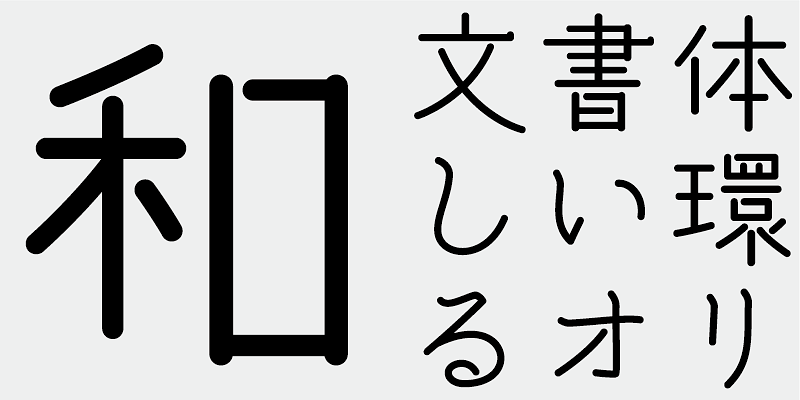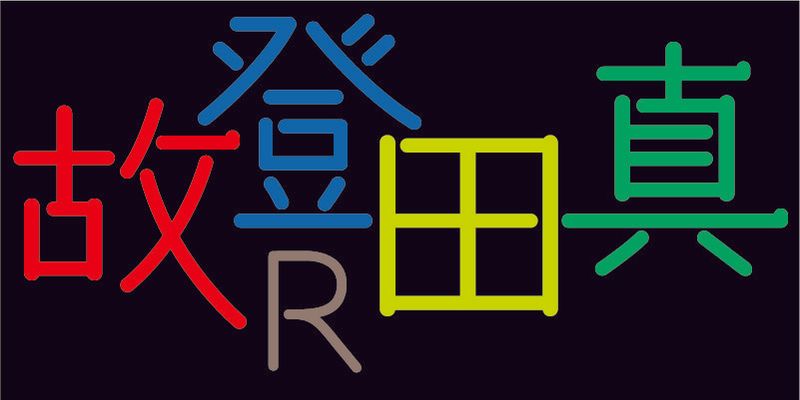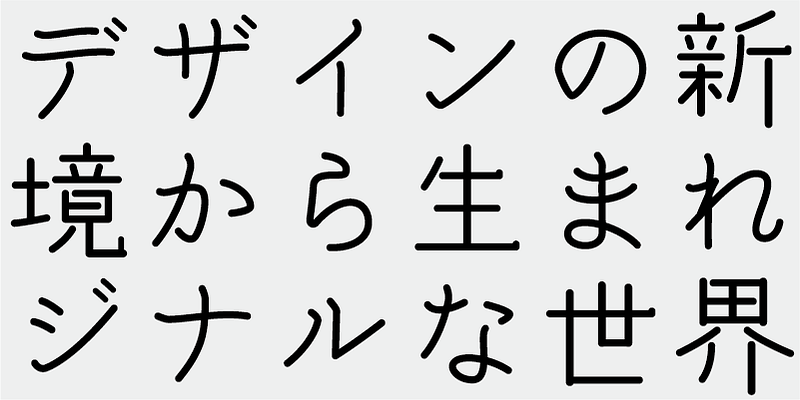
“캐주얼하고 편안한” 모양과 느슨한 문자 간격을 가진 둥근 모서리 고딕 서체입니다. 조판 텍스트는 시각적으로 부드럽고 차분한 표현을 연출합니다.
글꼴에는 Joyo Kanji List 및 Jinme-yo Kanji 문자의 2,286자 외에 가나 문자, 구두점, 라틴 문자 등을 포함한 206자가 추가로 포함되어 있습니다.
오늘날 일본어 글꼴 제작에서는 JIS 표준의 7,000자가 필수로 간주됩니다. 그러나 모든 글꼴에 정말 7,000자가 필요할까요? 사진 식자 시대에는 훨씬 적은 수의 문자가 필요했습니다. 독립 서체 디자이너 그룹인 FONT1000은 그 간단한 질문으로 시작했습니다. 일본어 서체에 필요한 최소 1,000자의 한자(표의 문자)를 선택했고 이를 지원하는 서체와 글꼴을 적극적으로 만들었습니다. 이 1,000자의 한자 문자 세트는 신문사, 출판사, 언어 연구 기관 등에서 수집한 문자 빈도 데이터를 사용하여 선택되었으며 가나 음절 문자 및 구두점도 포함합니다. FONT1000은 2001년에 25명의 디자이너와 25개의 서체로 시작했습니다. 현재는 130개의 서체를 보유 중이고 거의 40명의 멤버를 포함하도록 성장했으며, 더 많은 문자가 있는 글꼴 작업이 가능하게 되었습니다.